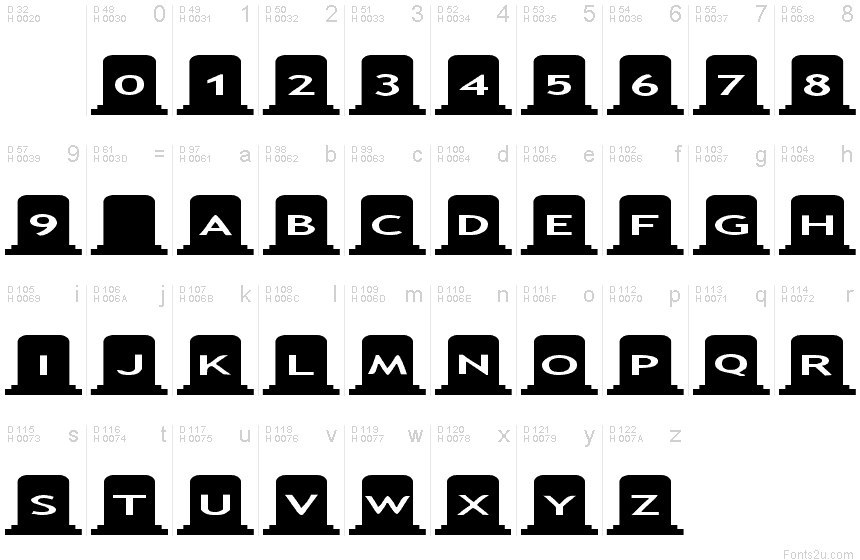
AlphaShapes Gravestones di Fonts n Things è un carattere display gratuito con un'atmosfera gotica e cupa fin dalle prime lettere. Le maiuscole sono costruite come blocchi di lapidi arrotondati, con basi a gradini e forme ritagliate, dando l'impressione di una fila di cippi cimiteriali piuttosto che di una normale scritta.
Questo rende questo font gratuito una scelta naturale per poster horror, volantini di case infestate, inviti a feste spettrali, merchandising stagionale e titoli che necessitano di poche parole. Funziona bene anche per l'apertura di capitoli, copertine e iniziali in stile monogramma, dove la silhouette della lapide è l'elemento principale.